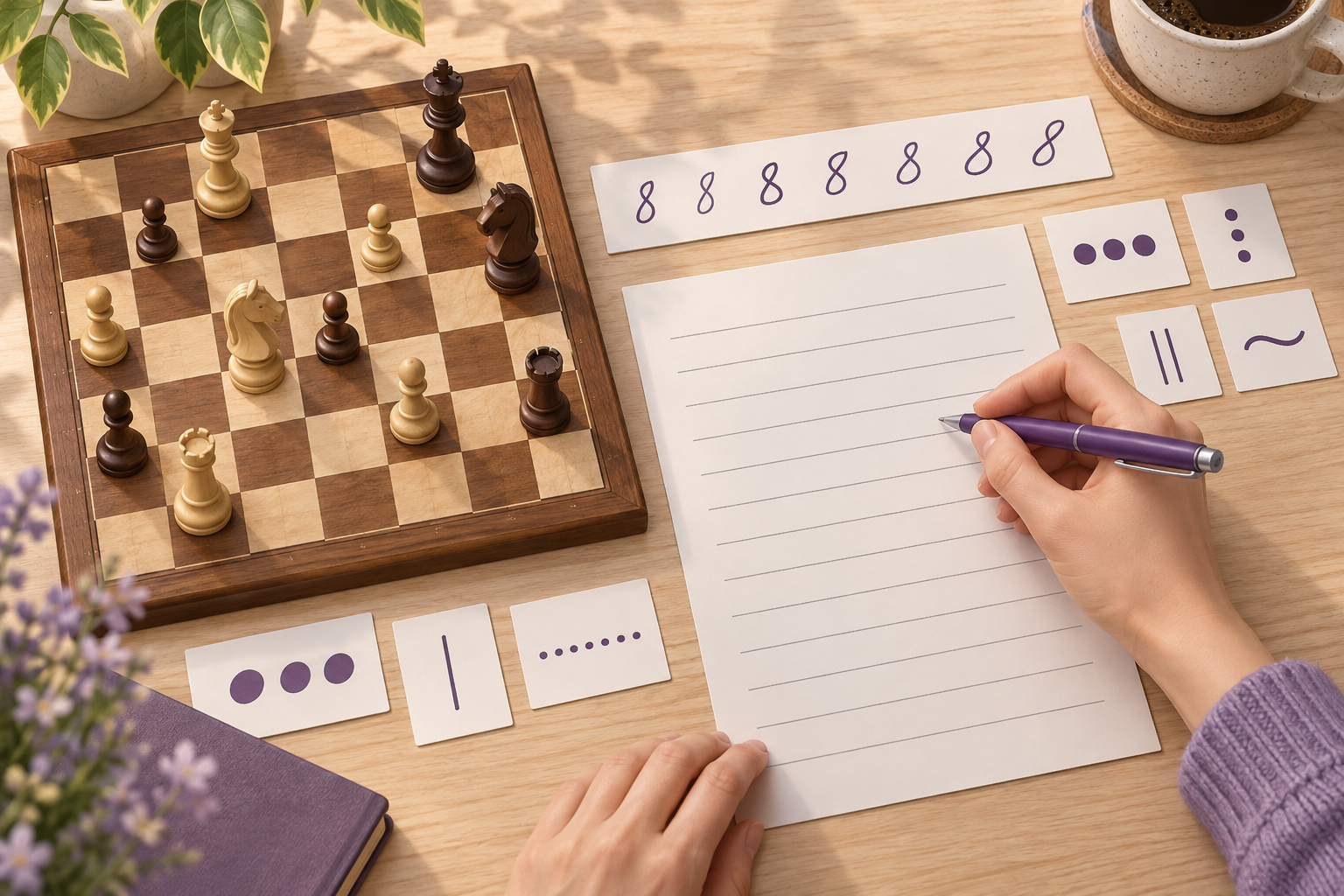
Рукописный шрифт для шахматной записи должен передавать не только характер букв: результат партии зависит от того, можно ли без догадок прочитать номер хода, координату поля, знак взятия и короткую пометку. Проверить набор помогает одна тестовая партия с разными ситуациями. Она выявляет путаницу между цифрами, пробелами и знаками раньше, чем вы соберёте длинный блокнот.
Почему шахматная запись — полезный тест для набора
В короткой записи шахматной партии рядом стоят буквы и цифры: Nf3, e5, Bxc6. Из-за этого ошибка одной цифры меняет поле, а не просто портит внешний вид строки. При этом тест касается нашего набора знаков: цифр 1–8, дефиса или тире для вариантов, точки после номера хода, многоточия для хода чёрных в сокращённой записи и строчных латинских букв a–h. Если вы проектируете кириллический рукописный шрифт, добавьте латиницу лишь тогда, когда она входит в реальную задачу проекта.
Запись удобна ещё и тем, что быстро показывает ритм. Одно и то же число то стоит отдельно (12.), то соседствует с буквой (e4), то завершает координату фигуры. Поэтому не ограничивайтесь листом с цифрами по одной: оценивайте их в осмысленной последовательности и в разных расстояниях между символами.
Какие части записи включить в тест
Возьмите компактный, но разнообразный фрагмент партии. Он должен проверять как минимум:
- номера ходов с точкой: `1.`, `12.` и двузначный `38.`;
- координаты с буквами обоих краёв доски: `a1`, `h8`, а также сочетания вроде `Nf3` и `Bb5`;
- ход пешки без буквы фигуры: `e4`;
- взятие, где используется латинская `x`: `Bxc6`;
- рокировку в принятом в проекте написании: `O-O` и `O-O-O`;
- варианты и примечания, если они будут в материалах: например, скобки или короткий знак вопроса.
Это не означает, что все перечисленные элементы обязаны войти в любой шахматный шрифт. Сначала решите, какой именно материал вы хотите набирать: запись ходов, учебные диаграммы, комментарии к партии или блокнот для анализа. Затем проверяйте только нужные формы и знаки. Тест становится полезным, когда он отвечает на конкретный сценарий, а не превращается в случайный каталог символов.
Не смешивайте требования нотации и стиль издания
FIDE описывает алгебраическую нотацию в приложении C к Правилам шахмат: поле задаётся сочетанием строчной латинской буквы файла и номера горизонтали, а ход фигуры записывается сокращением её названия и поля прибытия. Для английской записи используется N для коня, чтобы не путать его с королём K; правила также допускают привычные национальные сокращения фигур. Это помогает составить проверочную строку, но не диктует характер вашего рисунка или интервалы в дизайнерском макете. Официальные Правила шахмат FIDE
Формат учебника, журнала или авторского блокнота может включать редакторские знаки, варианты и подписи. Не выдавайте типографическое оформление комментариев за обязательную часть правил. Разделите таблицу требований на три колонки: знак, зачем он нужен в вашем проекте, откуда взят. Так вы не добавите десятки редко используемых символов «на всякий случай» и не будете приписывать FIDE рекомендации, которых в правилах нет.
Проверьте цифры внутри координат
В шахматной записи цифры 1–8 появляются рядом с буквами a–h. Пара b1 должна мгновенно читаться как координата, а не как слово или сокращение. Поэтому смотрите на формы цифр в двух окружениях: отдельно (1 2 3 4 5 6 7 8) и в поле (a1 b2 c3 ... h8). Не копируйте весь квадратный массив, если строка получается слишком плотной; достаточно выбрать края диапазона и несколько средних сочетаний.
У цифр 1 и 7 проверьте направление верхнего штриха и основание: в малом кегле они часто теряют отличие. У 3 и 8 сравните открытость и плотность, у 5 и 6 — место перехода дуги в прямой штрих, у 0 и 8 — наличие перетяжки. Здесь полезно показывать тест людям, не знающим, какое поле задумано: контекст партии способен подсказывать ответ и скрывать слабую форму.
Проверьте и двузначные номера ходов. В записи 38. обе цифры должны сохранять собственные очертания, а точка не должна прилипать к последнему знаку. Сравните визуальную длину 8. и 38.: точка остаётся частью номера, но интервал до следующего хода должен дать строке дышать.
Согласуйте строчные латинские буквы с цифрами
Координатная запись смешивает буквы файла и цифры ранга, поэтому важны не только цифры. Особенно внимательно проверьте пары, в которых рукописная латинская a может напоминать кириллическую «а», а h — похожую на элемент другой буквы. Если шрифт будет использоваться в международном наборе, убедитесь, что латинские и кириллические формы сознательно различаются или сознательно унифицированы. Не рассчитывайте на то, что читатель всегда вспомнит язык подписи.
Соберите короткие контрастные примеры: a1, g7, Nf3, Bb5, h8. Распечатайте их рядом с русскими словами и обозначениями, которые реально встретятся в тексте. Это выявит случайные сходства в общей строке, хотя отдельный лист с латиницей может выглядеть безупречно.